У слов есть власть, а типографика — их голос На протяжении веков голос был таким, как мы «слышим» то, что мы читаем. Также обычно понимается, что шрифты и типографика являются основным элементом брендинга, выражения, вокального диапазона. Хорошая типографика влияет на понимание, настроение и значение бесчисленными способами и является неотъемлемой частью дизайна.
Но сегодня появилось нечто, что может сдвинуть парадигму.
Вариативный шрифт — это один шрифт, который действует как много
— Джон Хадсон
Появление Variable Fonts изменяет всю динамику. Как описал Джон Хадсон, переменный шрифт — это один шрифт, который действует как много: все вариации ширины и веса, наклона и даже курсивности могут содержаться в одном, очень эффективном и сжимаемом файле шрифта.
Более того: формат (который является технически частью спецификации OpenType 1.8) является полностью расширяемым. Конструктор типов дает полный контроль над тем, какие оси используются, их диапазоны и даже определение новых осей.
В настоящее время существует 5 «зарегистрированных» осей (ширина, вес, наклон, курсив и оптический размер), но дизайнер может варьировать любую ось, которую выберет. Некоторые примеры включают в себя высоту восходящих и десендеров, класс текста, даже форму засечки.
Возможности практически безграничны. Удалив барьер производительности, мы открываем дверь для более интересного и динамичного дизайна, и гораздо большей способности выражать истинный голос бренда. Все это при сохранении верности самому шрифту: могут быть изменены только оси, выставленные дизайнером. Искусственное искажение не допускается.
Заново изобретенный веб-дизайн
Несмотря на то, что технология все еще зреет, а типовые дизайнеры работают над тем, чтобы использовать новый способ работы более эффективно, это новаторство может здорово повлиять на веб-дизайн в целом. Типичным сценарием было бы ограничить любой данный дизайн 3-5 различными шрифтами, чтобы представлять каждый аспект языка дизайна и голоса сайта, включая отдельные блоки текста и заголовков. В своей простейшей реализации переменные шрифты дают нам свободу использовать разный вес для каждого уровня заголовка, что значительно увеличивает их ясность и удобочитаемость.
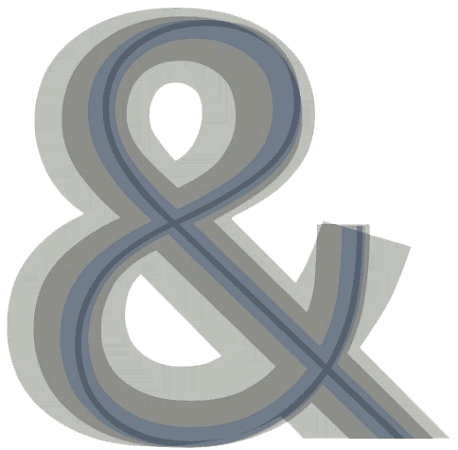
Также можно использовать более узкие ширины символов для заголовков, или там, где данные располагаются более плотно. Фактически вся типографская система может быть спроектирована пропорционально: вес и ширина могут стать мультипликаторами на стандартных настройках основного текста. Это позволит легко масштабировать эти аспекты вместе текстом, если его параметры изменяются в зависимости от размера экрана или предпочтений пользователя. Все это сопровождается увеличением производительности из-за меньшего количества HTTP-запросов (меньше файлов шрифтов) и общей экономии загружаемых данных (хотя это зависит от используемого шрифта и сжатия).
Все это открывает возможности быть более выразительными, а некоторые из действительно интересных функций помогут преобразовать сам опыт чтения.
Чтение на экране
Шрифт должен сделать больше, чем выглядеть красиво: он должен работать сложно.
-Эрик Шпикерманн
Некоторые из самых больших проблем в создании хорошего опыта чтения связаны с отсутствием изящества в пропорции и мелких деталях. Вариация современных функций CSS и OpenType представляет собой мощную комбинацию. Возможность устанавливать такие функции, как лигатуры и перенос слов на основе языка, включать и отключать перенос на основе размера экрана и даже настраивать ширину символа на самых маленьких экранах, чтобы соответствовать большему количеству символов в строке без уменьшения размера шрифта, может значительно улучшить гладкость и комфорт чтения.
Экскурс в историю
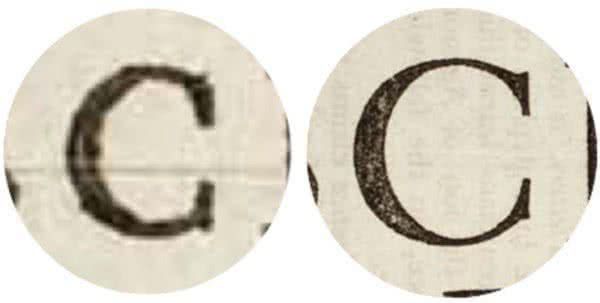
Первое изображение имеет размер 6pt, второе — 72. Обратите внимание на разницу в контрасте хода. Он намного более утончен в больших размерах.
Еще одна особенность, характерная для старой печати, но потерянная при переводе на фотопечать и цифровую печать — оптическая калибровка (некоторые дизайнеры все еще создают отдельные оптические размеры для разных диапазонов, но редко). Не так часто встречается в конструкциях без засечек, но в последние десятилетия (по правде говоря, на протяжении веков) было довольно распространено: задавать физически меньшие размеры шрифта, а в некоторых случаях даже более широкие апертуры, чтобы сохранить читаемость. Газеты, в частности, обнаружили, что это важно, чтобы линии не терялись, или письма не слишком сильно страдали от увеличения количества чернил.
Оптическая калибровка вернулась в переменных шрифтах, и может автоматически применяться там, где это возможно, или явно указывается веб-дизайнером или разработчиком. Как уже упоминалось, это не такая частая особенность шрифтов без засечек, но может быть использована для некоторого эффекта в дизайне с засечками, с более высоким штрихом.
Все эти преимущества убеждают работать с вариативными шрифтами. Но хорошая типографика — не все, что нужно для великолепного дизайна. Диапазон осей, таких как ширина и вес, дает нам огромную свободу. При этом нам не надо загружать чрезмерное количество файловых активов. И так как у нас уже есть эти несколько требуемых переменных шрифтов, нужно начать их широко использовать вместе с создателями контента. Представьте себе роль дизайнеров внутри Системы управления контентом (или CMS), где размещается веб-сайт. Этот дизайнер мог бы использовать некоторые простые элементы управления, встроенные в CMS, которые позволяли бы набирать определенные заголовки или блоки текста. Это вывело бы дизайн сайта на новый уровень, без необходимости писать собственный код каждый раз.
Мы все еще можем быть на заре этой новой эры, но это будущее. И оно, безусловно, очень яркое.
По состоянию на май 2018 года 3 из 4 основных веб-браузеров уже поддерживают переменные шрифты, в дополнение к доминирующим мобильным платформам (проверьте поддержку на caniuse.com). Имея это в виду, мы готовы начать улучшать Интернет уже сегодня.